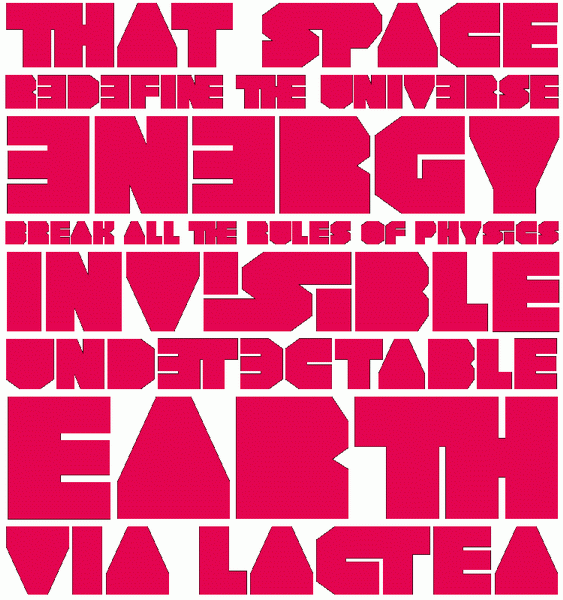
Eklipse por Rafael Neder
Adoro essas fontes que desafiam o limite do que é legível. Além de que o tratamento que Rafael Neder deu as ligaturas transformou a Eklipse em muito mais que uma fonte.